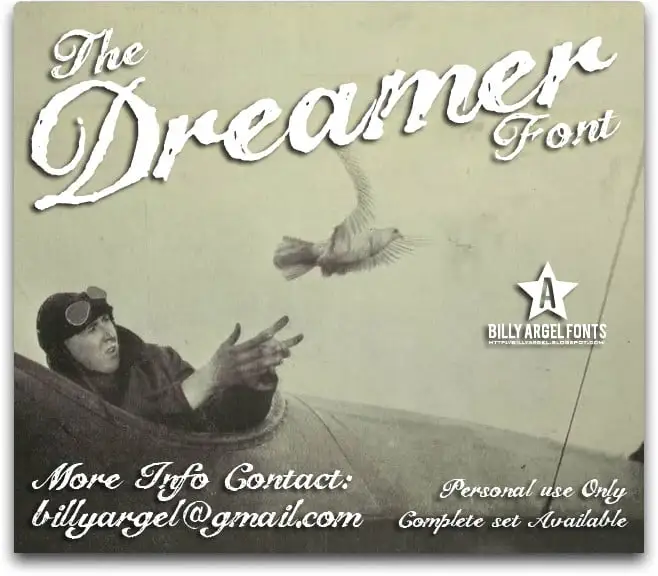
The Dreamer Script Font – Download Grátis
A fonte “The Dreamer Script Font” traz uma atmosfera envolvente e natural para quem busca expressar sua personalidade de maneira única no design de textos. Desenvolvida pelo designer Hamilton, esta fonte é perfeita para aqueles que buscam uma sensação romântica e poeticamente fluida em seus projetos gráficos. Embora seja livre apenas para uso pessoal, a fonte dispõe de opções de licenciamento comercial disponíveis. Se você está procurando por uma maneira criativa de incorporar esse charme na sua próxima peça de design, Hamilton oferece mais informações e um modo conveniente para entrar em contato através do site da Billy Argel Fonts. Para quem busca inspiração em fontes script, “The Dreamer Script Font” é uma excelente escolha. Suas linhas fluidas e o tom delicado que ela transmite tornam-na uma opção atraente tanto para projetos digitais quanto para trabalho impresso. Visite os sites de Billy Argel Fonts ou contate-os diretamente se estiver interessado em saber mais sobre suas possibilidades criativas.